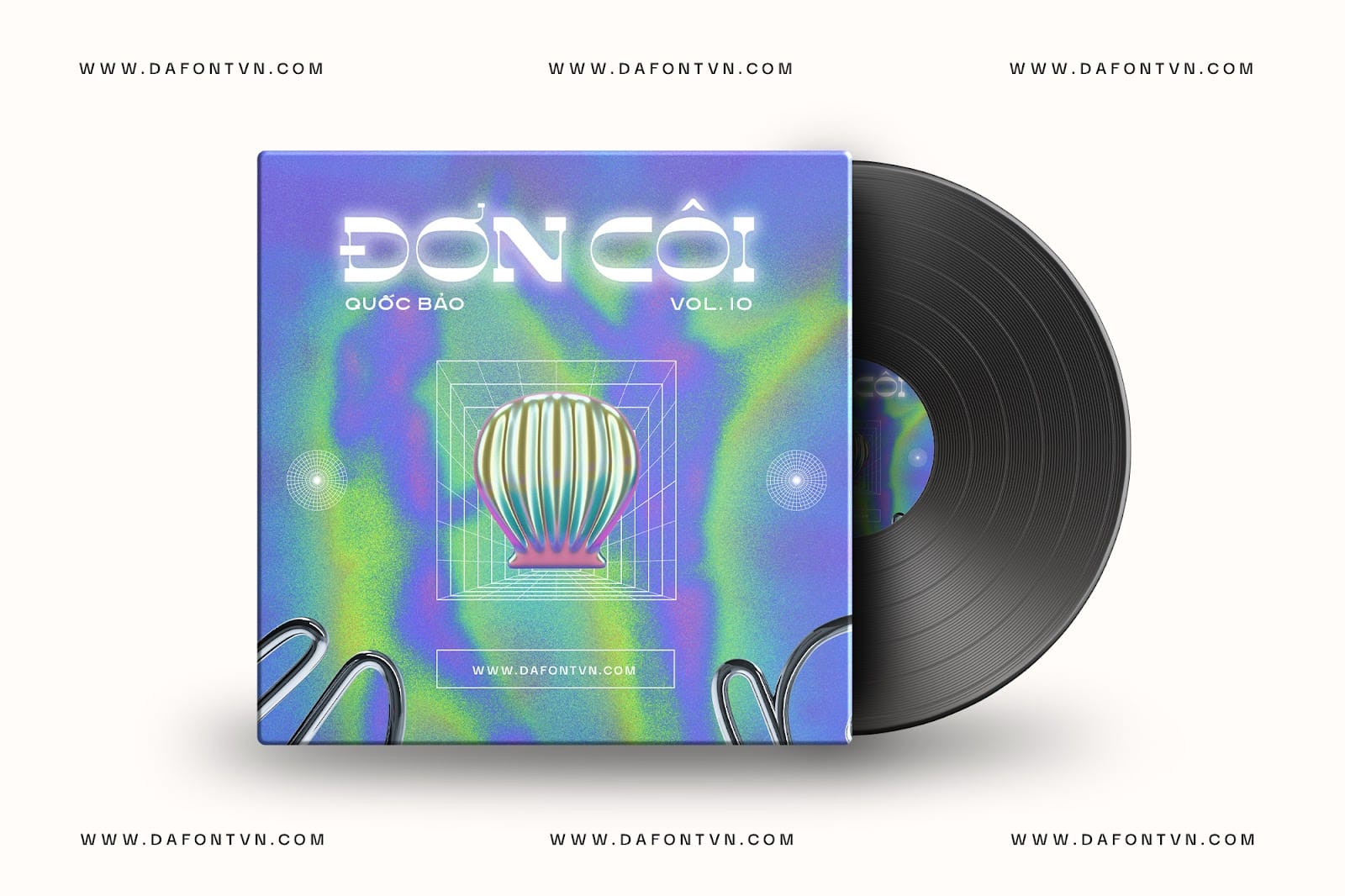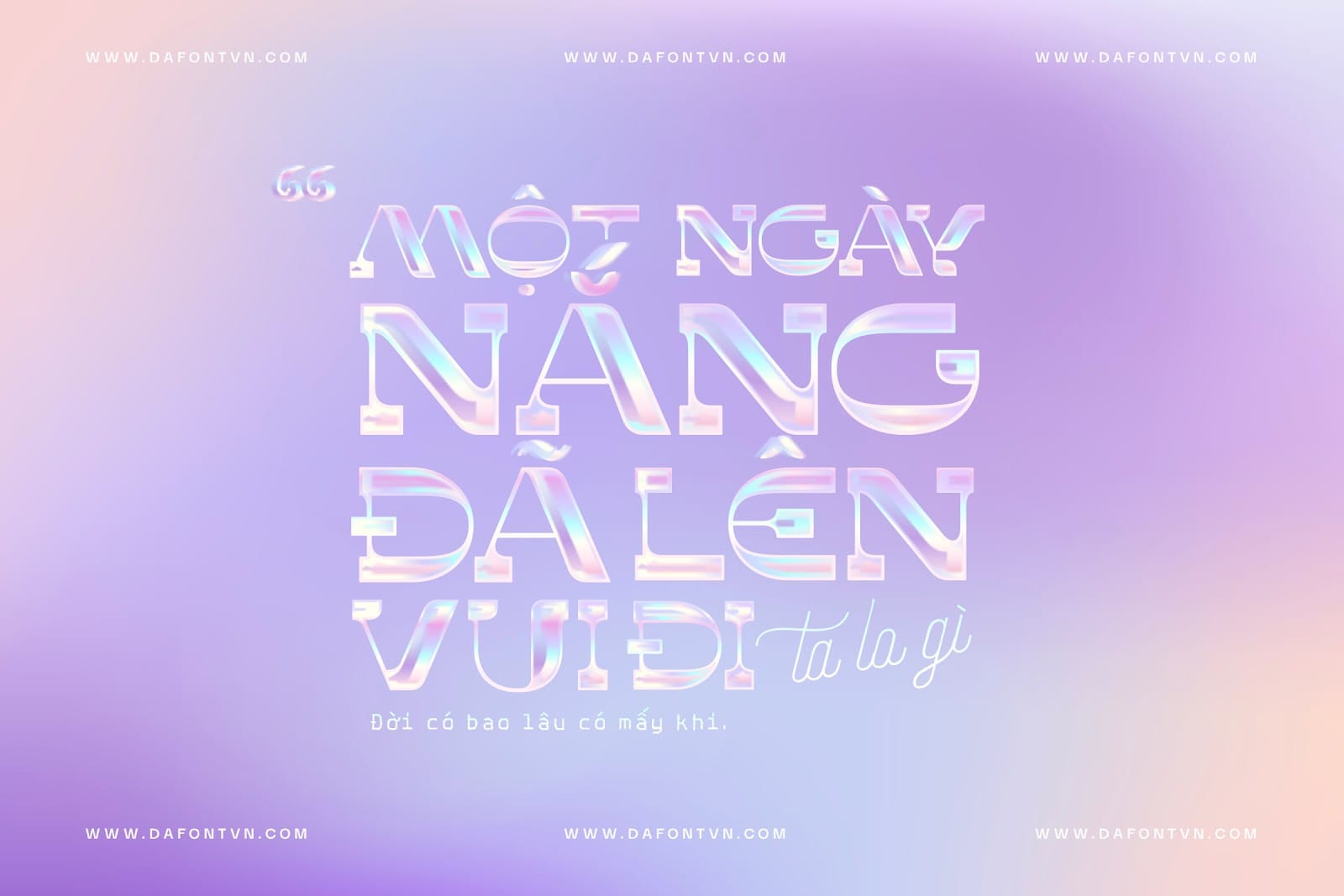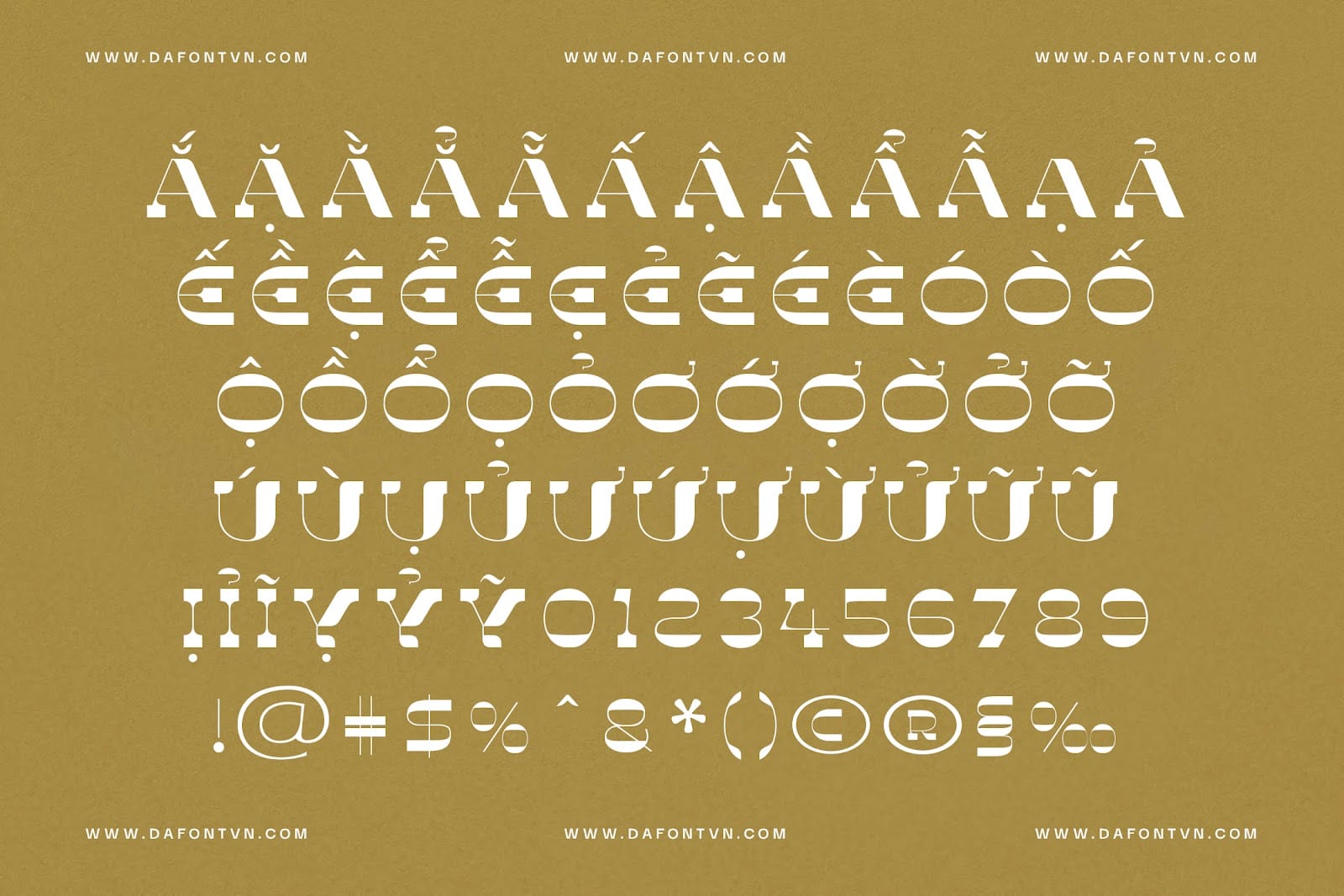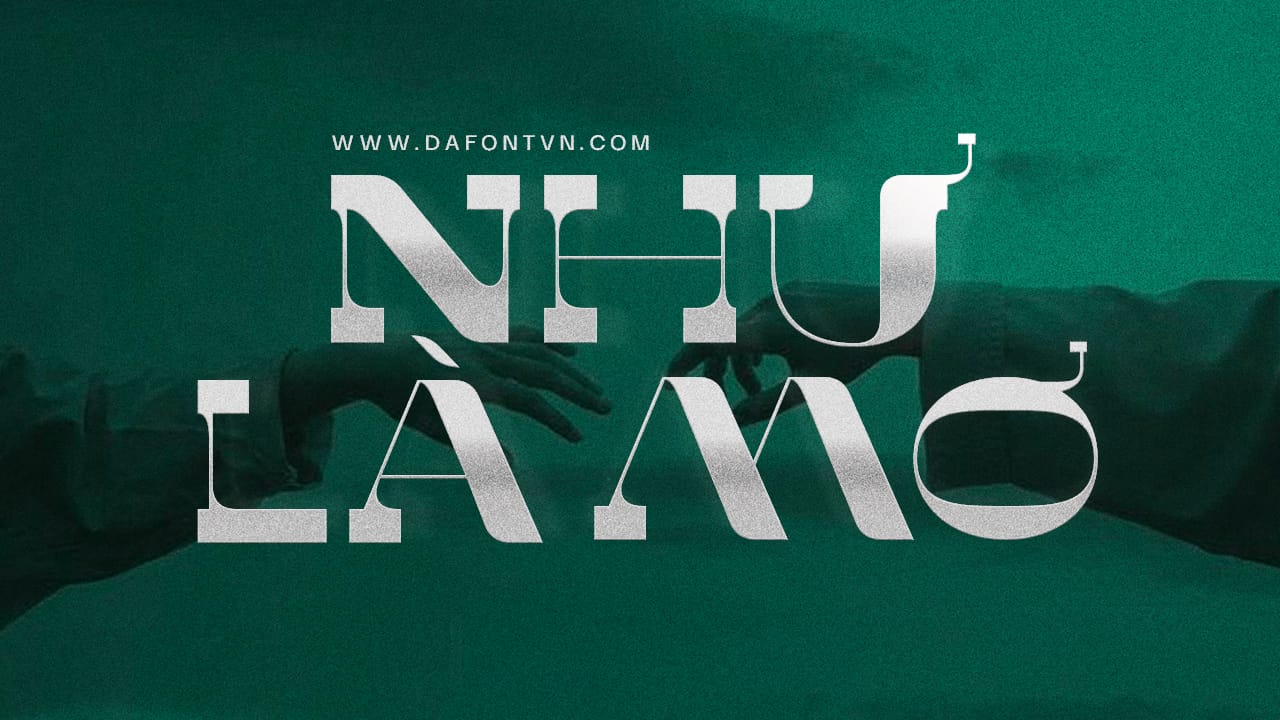
Kroma Display là kiểu chữ hiển thị với các nét được thiết kế cực ấn tượng và hiện đại. Kroma có thể được sử dụng cho nhiều thiết kế như logo, bìa tạp chí, thiệp mời, quảng cáo hoặc các dự án cần 1 kiểu chữ tiêu đề đẹp mắt với các đường viền có độ tương phản cao của font Kroma.Với 350 nét vẽ, Kroma Display cung cấp nhiều tùy chọn kiểu dáng, bản gốc của font với các dấu của chữ viết hoa và viết thường có đôi chút khác nhau vì vậy mình đã chỉnh sửa lại, mặc dù đã phân vân có nên để nguyên dấu hay không, nhưng cuối cùng chỉnh sửa lại để đồng nhất các ký tự khi gõ.